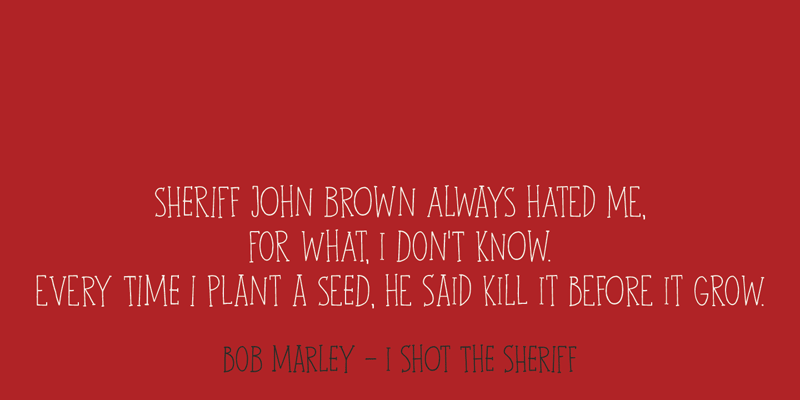
A nova fonte ‘DK John Brown Font’ traz uma vibe nostálgica e retro ao seu projeto. Desenvolvida pelo designer Hamilton, esta demo oferece um visual minimalista que combina perfeitamente com os estilos de texto retro, sem a necessidade de grandes recursos gráficos ou complexidades. Ideal para aqueles buscando uma fonte discreta com uma pegada mais vintage e elegante, ‘DK John Brown Font’ é perfeita para aplicar em materiais pessoais e projetos criativos onde um toque de nostalgia se encaixa bem. Independentemente do uso que você deseja dar a esta fonte, vale ressaltar sua natureza restritiva. Para o seu uso comercial, recomendamos adquirir a versão completa, que inclui ajustes kerning, direitos de embedding e todos os caracteres presentes no site da designer: hanodedfonts.com. Não se esqueça também de consultar a FAQ fornecida dentro do arquivo zip. Esta fonte não pode ser utilizada em jogos, aplicativos ou softwares comerciais sem uma licença adicional disponível no site da Hamilton ou em seu FAQ específico. Se você estiver interessado nesse tipo de permissão, não hesite em entrar em contato diretamente com ela para obter informações sobre as condições de uso e as oportunidades de compra.